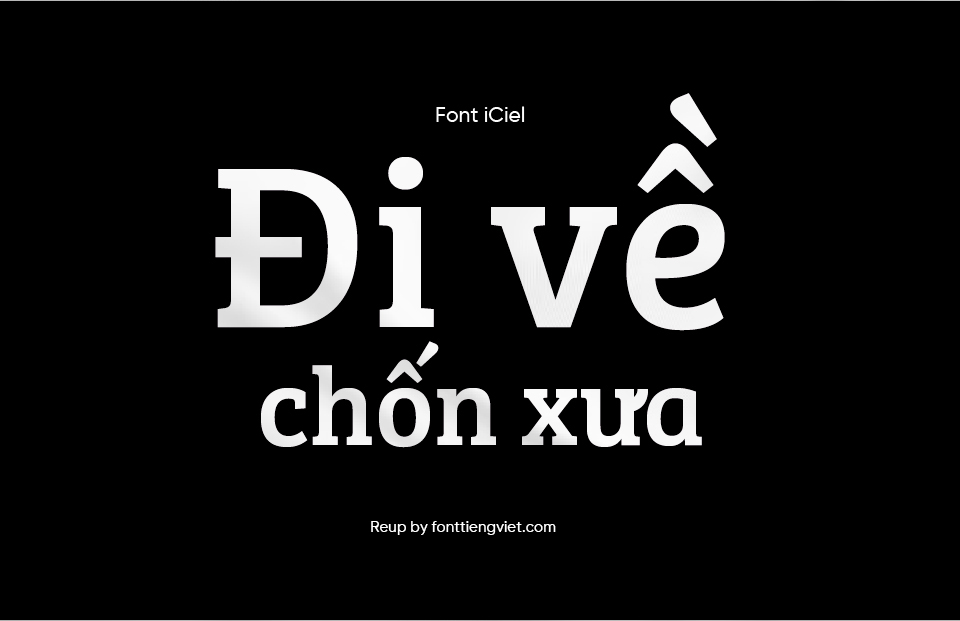
Giới thiệu về Font Việt hóa iCiel Bree
Trong thế giới đồ họa hiện đại, việc lựa chọn một Font Chữ phù hợp đóng vai trò quyết định đến sự thành công của một tác phẩm. Font Việt hóa iCiel Bree là một trong những bộ font được ưa chuộng nhất nhờ vẻ ngoài thân thiện, thanh lịch và cực kỳ dễ đọc. Được phát triển dựa trên bản gốc Bree của TypeTogether, phiên bản iCiel đã được tinh chỉnh kỹ lưỡng để hỗ trợ đầy đủ tiếng Việt, giúp người dùng không còn lo lắng về lỗi hiển thị dấu.
Đặc điểm nổi bật của Font Việt hóa iCiel Bree
Phong cách thiết kế tinh tế
Đặc trưng của bộ font này là sự kết hợp hoàn hảo giữa nét chữ viết tay mềm mại và cấu trúc hình học hiện đại. Các đường cong được bo tròn khéo léo tạo cảm giác trẻ trung, năng động nhưng vẫn giữ được sự chuyên nghiệp cần thiết. Chính vì vậy, Font Việt hóa iCiel Bree thường xuyên xuất hiện trên các bao bì sản phẩm, poster quảng cáo và giao diện ứng dụng di động.
Tính ứng dụng cao trong học tập
Đối với các bạn học sinh và giáo viên, bộ chữ này là công cụ đắc lực để thiết kế slide bài giảng hoặc làm báo cáo. Với độ dày nét vừa phải, chữ iCiel Bree giúp nội dung trở nên trực quan, giúp người xem dễ dàng tiếp nhận thông tin mà không bị mỏi mắt. Bạn có thể sử dụng font này cho cả tiêu đề lẫn đoạn văn bản ngắn một cách linh hoạt.
Cách sử dụng Font Việt hóa iCiel Bree hiệu quả
Để phát huy tối đa vẻ đẹp của font, bạn nên kết hợp nó với các tông màu sáng hoặc pastel. Trong các dự án thiết kế, việc sử dụng iCiel Bree làm tiêu đề chính sẽ tạo điểm nhấn thu hút ngay từ cái nhìn đầu tiên. Hãy đảm bảo bạn đã cài đặt đúng định dạng để trải nghiệm trọn vẹn sự mượt mà của bộ font này.